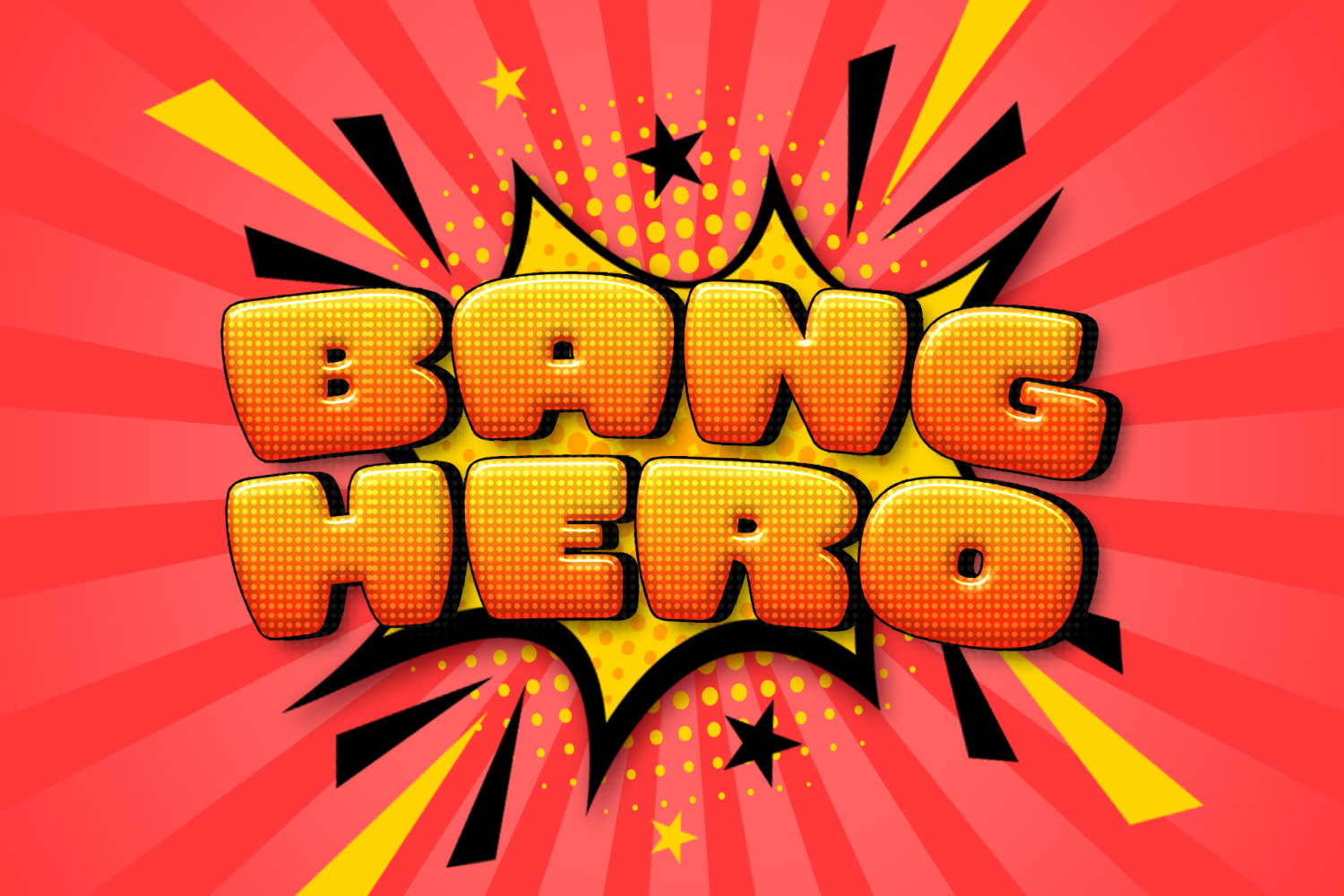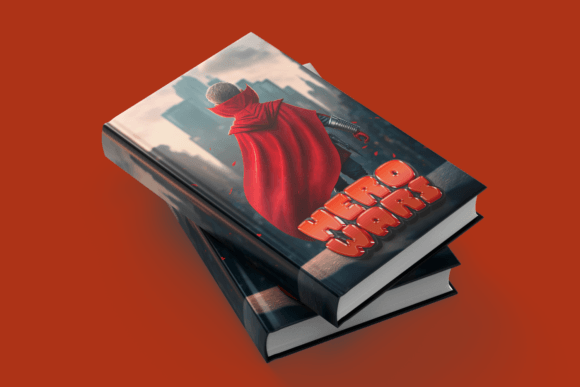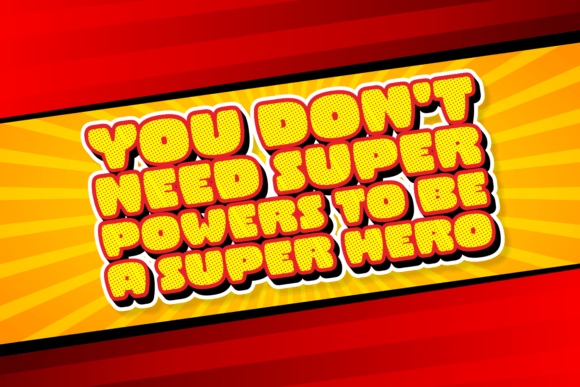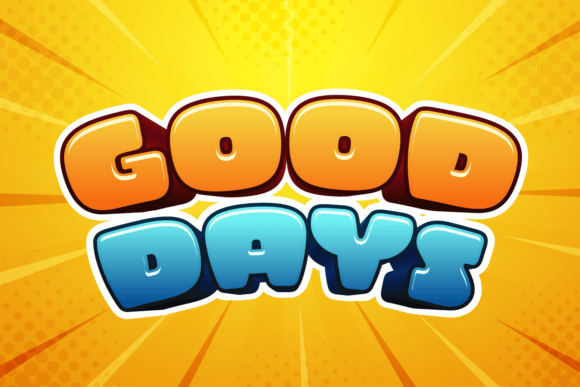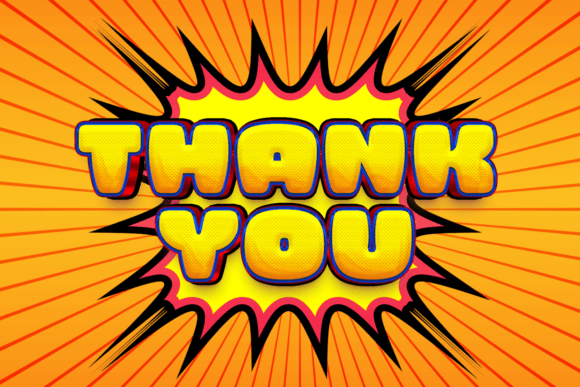
فونت Bang Hero انگلیسی
| ⭐ توضیحات | Bang Hero یک فونت نمایشی سرگرم کننده به سبک کمیک است. بازیگوش و درشت، این مجموعه از شخصیت ها انتخاب مناسبی برای پروژه های طراحی شما است. هر زمان که نیاز به ایجاد تایپوگرافی برجسته داشتید از آن استفاده کنید تا همه کسانی که آن را می بینند تحت تاثیر قرار دهد. |